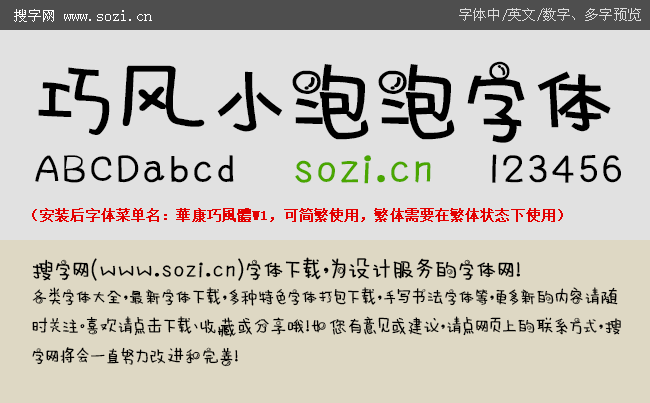
巧風(fēng)小泡泡字體
搜字網(wǎng)給大家提供一款巧風(fēng)小泡泡字體手機(jī)中文字體下載。這款手機(jī)中文字體以華康巧風(fēng)體為原形,將一些筆畫的點(diǎn)改成了可愛泡泡圖形,華康巧風(fēng)體是一款美術(shù)風(fēng)格的繁體字庫,摘自華康最新出品的《華康手書風(fēng)II-字得其樂》,經(jīng)過改造后更加卡通化,增加了趣味性,非常適合喜歡個(gè)性的朋友在手機(jī)上安裝使用。